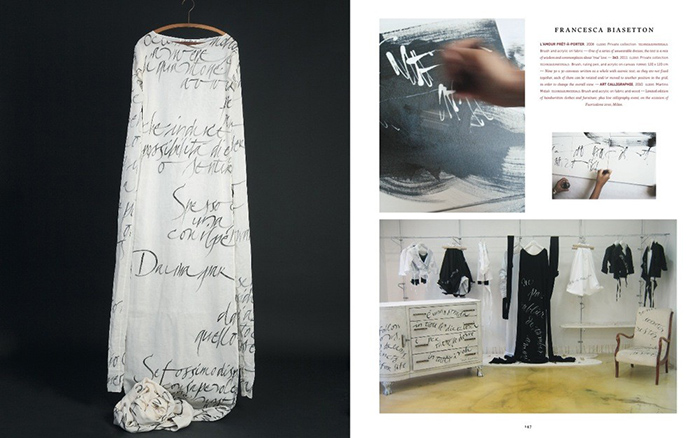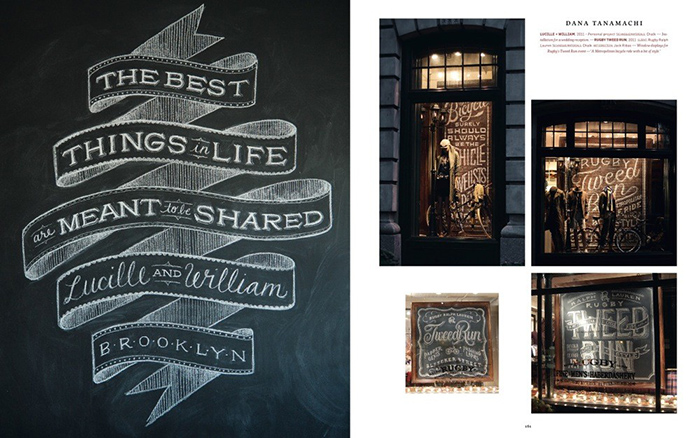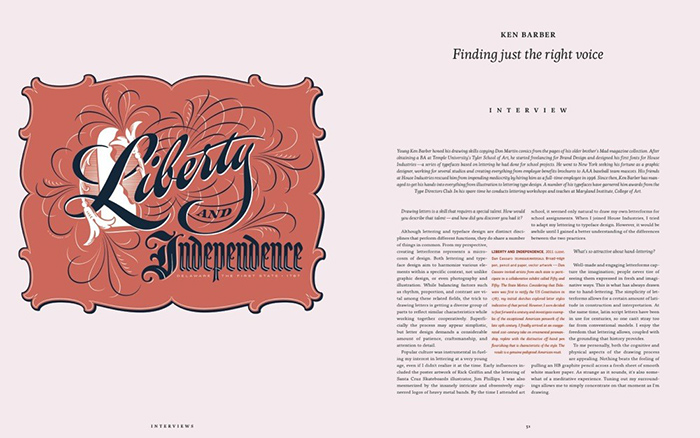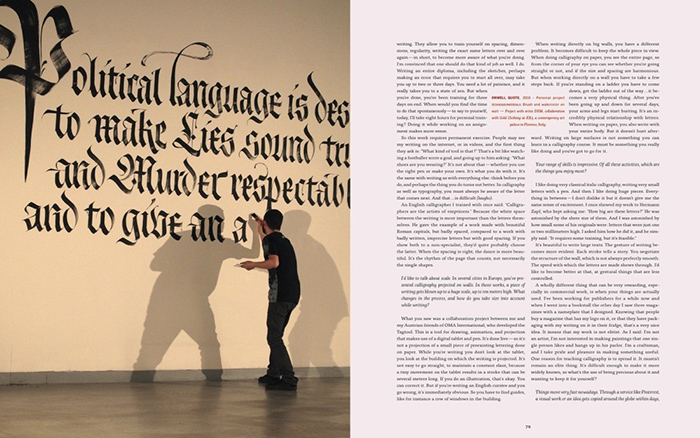
»Hand to Type« von Jan Middendorp ist ein Zusammenstellung der Arbeiten von zeitgemäßen Designern und Künstlern, die sich speziell mit kalligrafischer Schriftgestaltung auseinandersetzen. Auf über 100 Seiten werden die Gestalter, ihre Arbeiten und Arbeitsweisen vorgestellt. Daneben gibt es im Buch Interviews und Essays. Das Buch ist komplett in Englisch und erschien 2012 im Berliner Gestalten-Verlag.
Wer sich für kalligrafische Schrift interessiert, findet in diesem Buch eine umfassende und hervorragend aufbereitete Zusammenstellung aktueller Arbeiten. Diese werden großformatig in bester Qualität präsentiert und die Essays und Interviews reichern die Darstellungen mit interessanten Hintergrundinformationen zum Thema an.
Inhalt
- Vorwort von Jan Middendorp
Writing Culture – Expert Essays –
- Patrick Griffin: alphabets from parallel unviverses
- Shoko Mugikura: japanese writing
- Kimya Gandhi & Dan Reynolds: the many faces of india
- Alexei Vanyashin: cyrillic
- Nadine Chahine: what arabic is and what it is not
- Florian Hardwig: kurrentschrift
- Ramiro Espinoza: the “amsterdamse krulletter”
- Rick Cusick: hallmark – influences and inspiration
[*]Interviews
- Ken Barber
- Timothy Donaldson
- Tony di Spigna
- Gemma O’Brian a.k.a. Mrs Eaves
- Luca Barcellona
- Niels Shoe Meulman
- Reza Abedini
- Brody Neuenschwander
- Garbiel Martínez Meave
[*]Portfolios & Processes
[*]Index of featured artists
Untertitel: Scripts, Hand-Lettering and Calligraphy